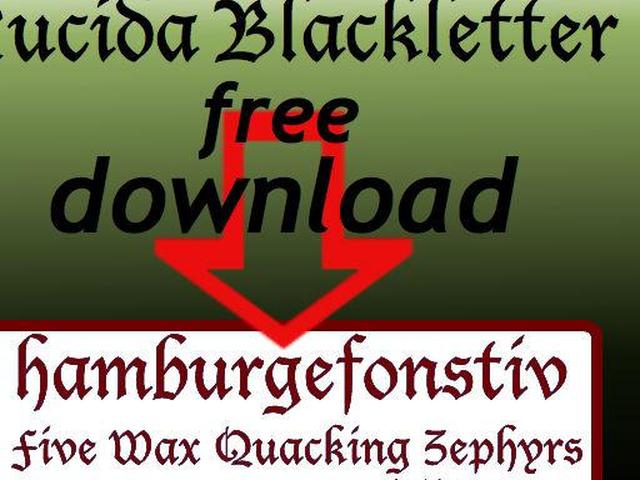
Найти бесплатный шрифт Lucida Blackletter в Интернете не так уж сложно, так как это один из самых популярных и старых шрифтов для настольных издательских систем. Тем не менее, вы можете изучить варианты, прежде чем выбрать Lucida Blackletter.
Lucida: семейство шрифтов
Lucida была разработана в середине 80-х — на заре настольных издательских систем, когда бушевали войны Helvetica, а Apple и Microsoft пытались конкурировать с Adobe за создание типографского стандарта. Чарльз Бигелоу и Крис Холмс, дизайнеры шрифтов, в конечном итоге создали большое семейство шрифтов Lucida в четырех гарнитурах:
- Script (содержащий Blackletter, Calligraphy и Handrwriting)
- Serif (шрифты Fax и Bright)
- Без засечек (Sans, Grande, Sans Typewriter и Sans Unicode)
- Математические символы TeX (Lucida — один из немногих полных шрифтов для математики)
Сценарий Blackletter
Как и большинство рукописных шрифтов, шрифт Blackletter столь же драматичен, как и звучит, с толстыми готическими штрихами, напоминающими средневековое каллиграфическое перо, которым владеет какой-нибудь строгий монах, кропотливо копирующий иллюминированную рукопись. Добавленный в семейство Lucida в 1992 году, он считается «курсивным», а также черным шрифтом. Существует много форм «черных» шрифтов — почти все они основаны на каллиграфических формах 16 века. На самом деле, одна из форм textualis, использованный Иоганном Гутенбергом для первой печатной книги. По этой причине Lucida Blackletter придает любой надписи ощущение формальности и фантазии. Несмотря на то, что в средние века блэклеттер использовался для больших блоков текста, современные глаза привыкли к гораздо более простым шрифтам. Lucida Blackletter — это то, что можно использовать для выделения заголовков, заголовков или баннеров, которые обычно не используются в реальных документах.
Шрифт также имеет тенденцию ассоциироваться с германским наследием, поскольку версия Blackletter под названием Fraktur использовалась почти исключительно в немецких исторических документах в средние века и в эпоху Возрождения. Кроме того, многие готические романтические сказки, такие как Дракула , использовали версии этого шрифта для украшения своих обложек, поэтому любые слова, напечатанные в них, могут иметь жуткий или драматический оттенок. Ни одно из этих качеств не обязательно является плохим, но о них следует помнить, когда вы используете бесплатный шрифт Lucida Blackletter.
Альтернативы Люсиде Блэклеттер
Тем не менее, вы, возможно, захотите попробовать некоторые альтернативы Lucida Blackletter, которые сохраняют дух шрифта и в то же время демонстрируют некоторые творческие таланты современных шрифтографов. семейства в DaFonts ( сайт бесплатных шрифтов) есть много примеров шрифтов в стиле блэклеттер, от очень чистого и крупного «Cloister Black» до более богато украшенного и стилизованного «Dirt2 Soulstalker». Эти шрифты используются не только для графики веб-сайтов или полиграфического дизайна; часто шрифты blackletter также являются любимыми надписями для тату-мастеров, придавая классическое байкерское ощущение надписям на коже. Независимо от того, для чего вы его используете, Lucida blackletter или любой из его собратьев будет выделяться впечатляющим историческим влиянием.